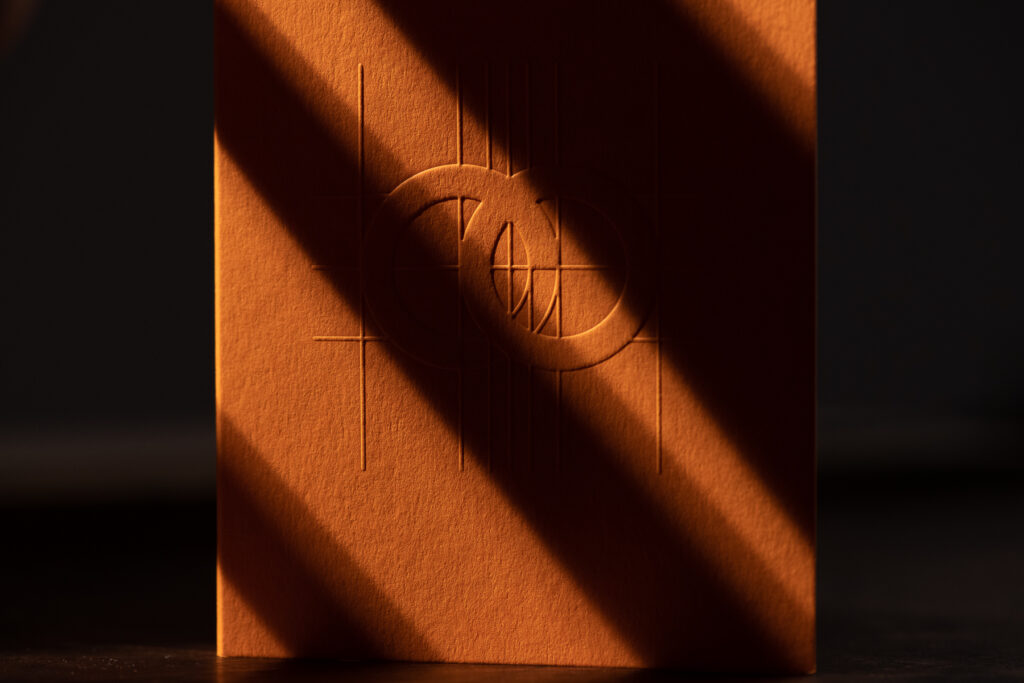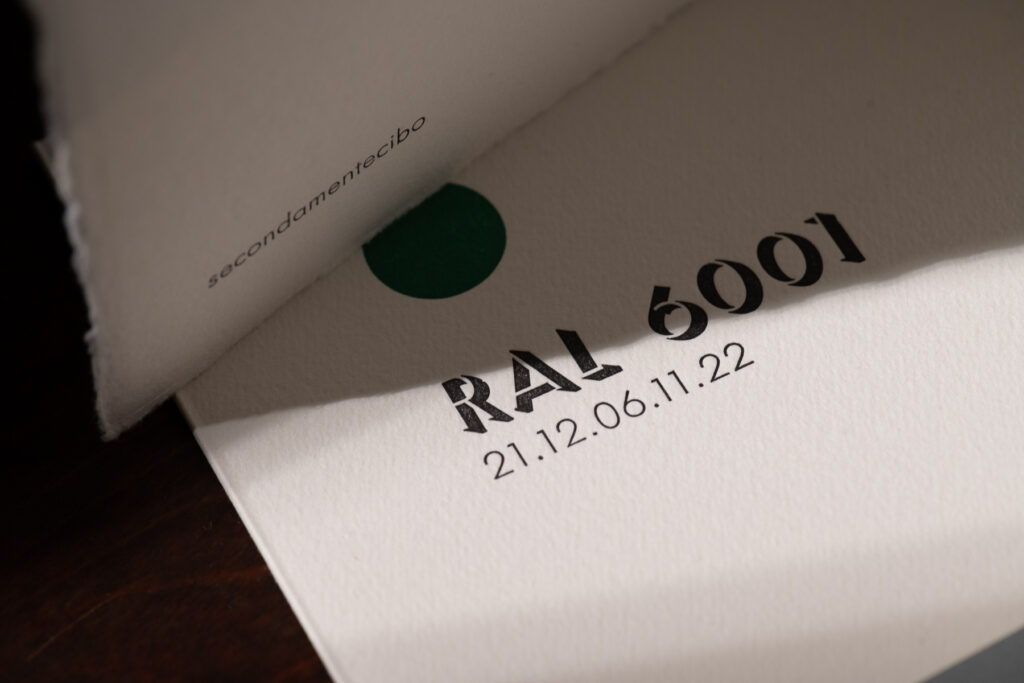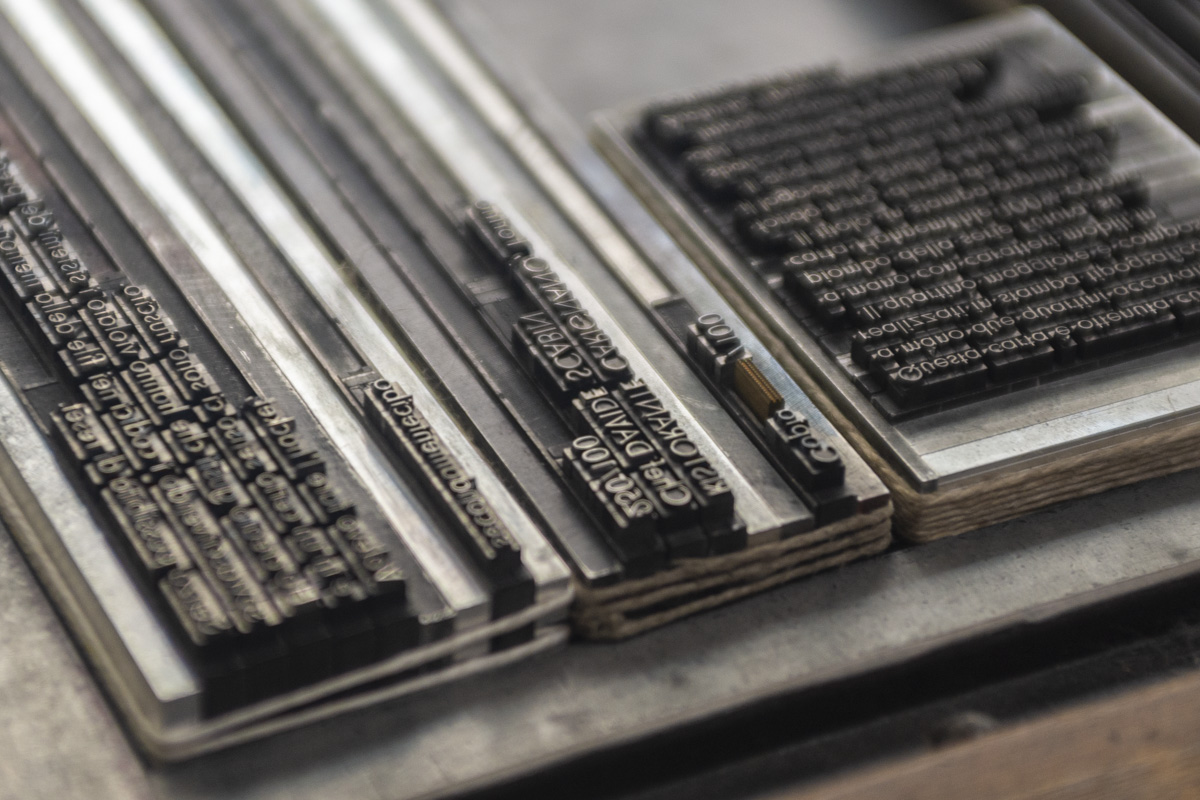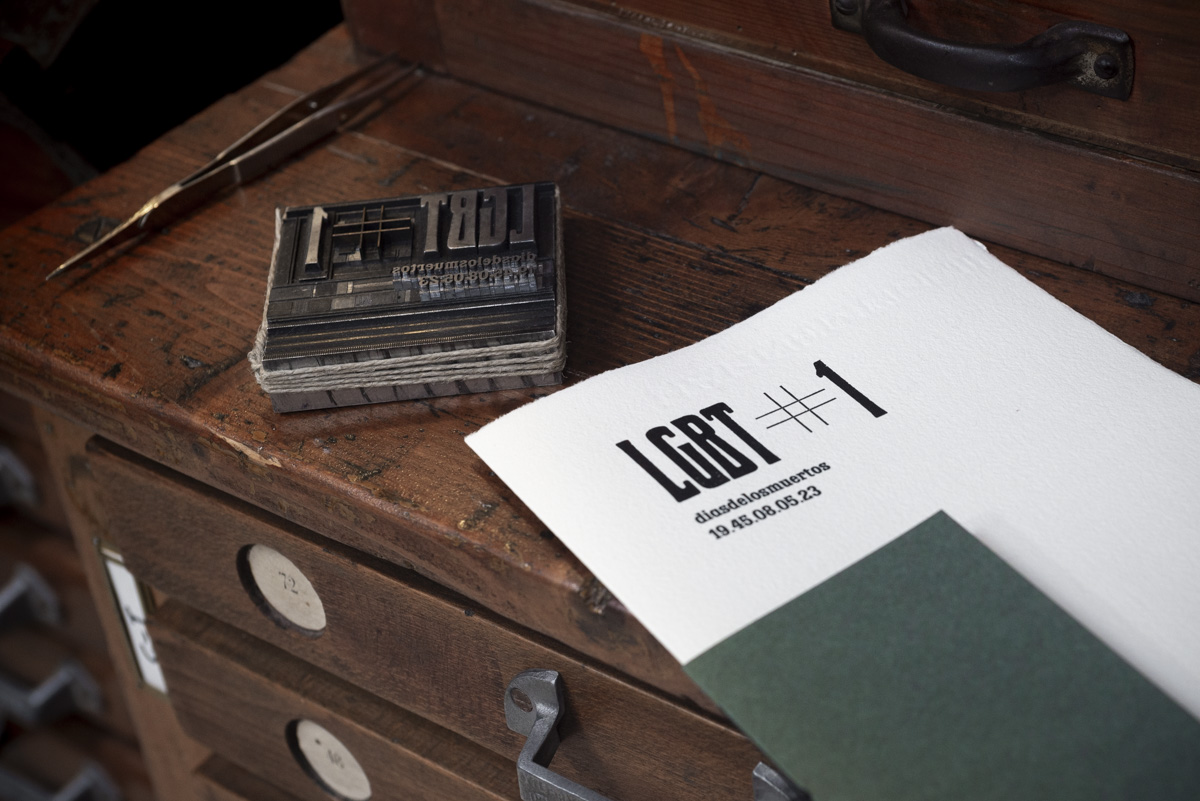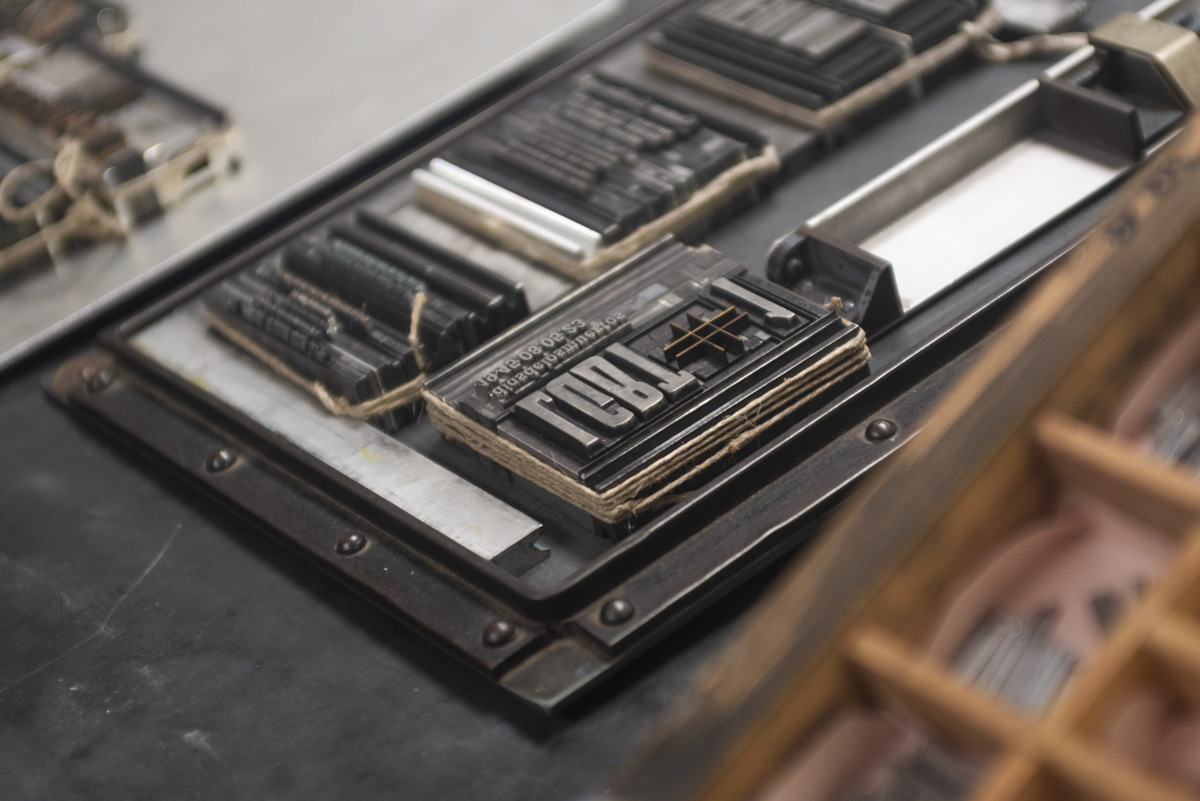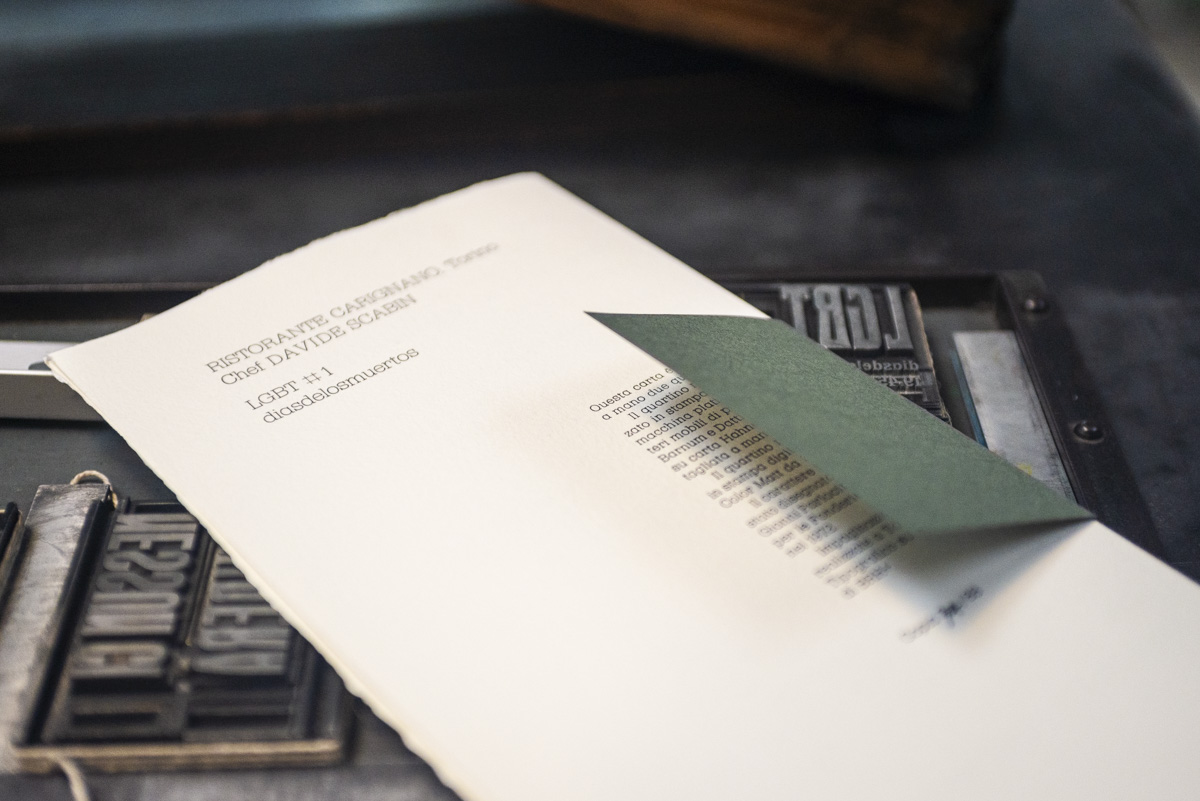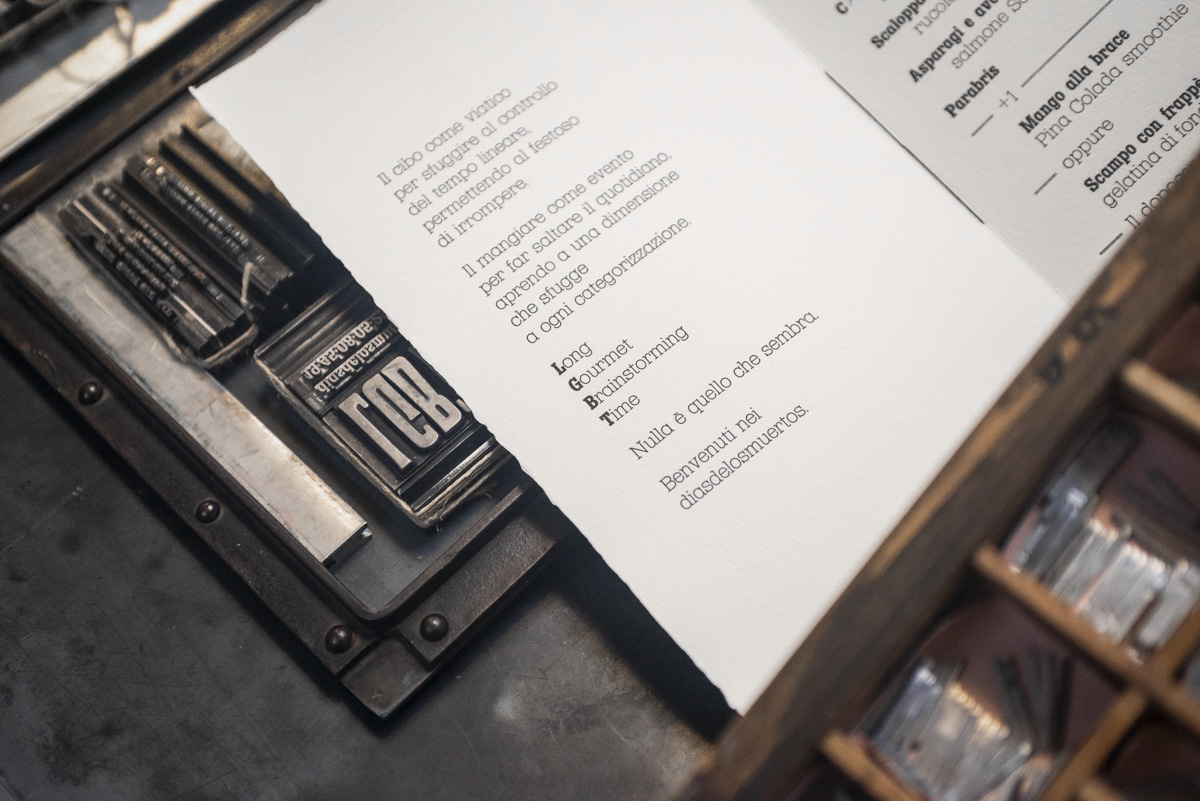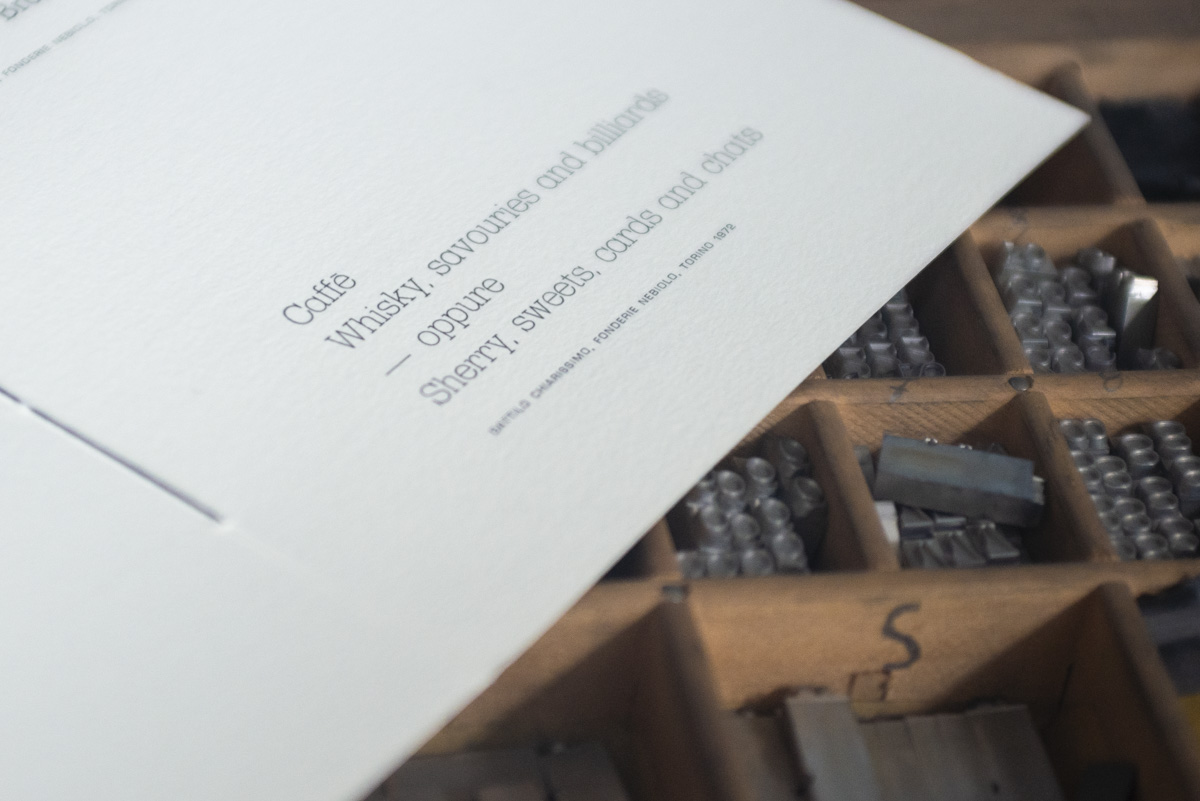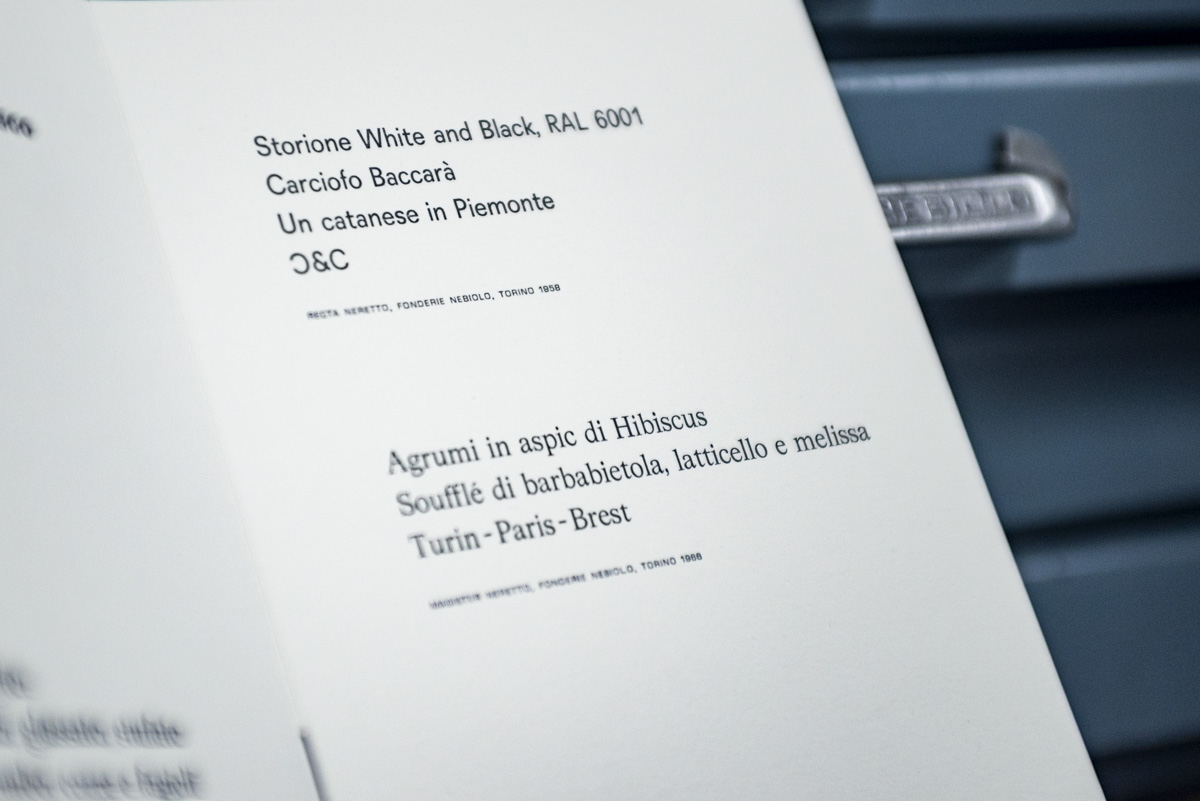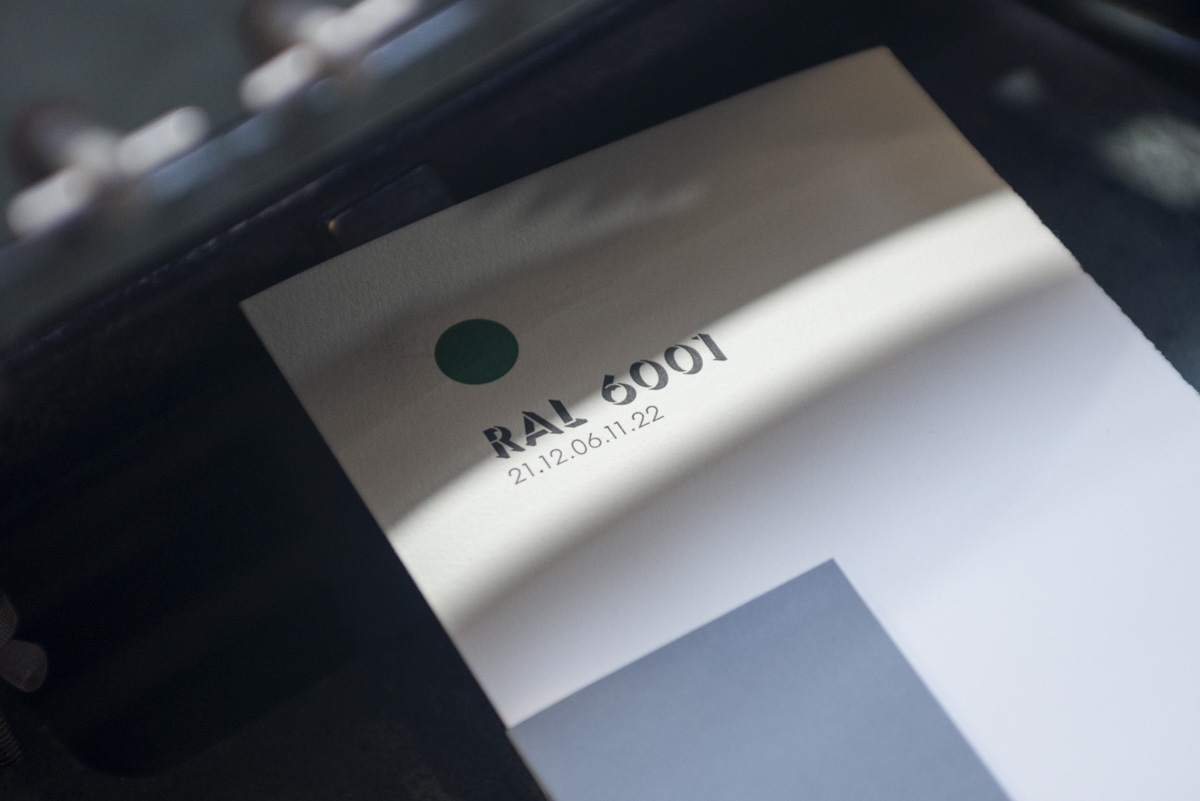
Dal 2024 Archivio Tipografico si occupa della realizzazione dei menu dello Chef Scabin per Ristorante Carignano, sotto la direzione artistica di BRH+.
Tutti i menu sono sempre interamente composti a mano con caratteri mobili in piombo o legno, su carta 100% cotone.
Riprendendo gli elementi visivi da un mondo che solitamente appartiene al mondo della stampa d’arte vengono realizzati dei menu in tiratura limitata e numerata per accompagnare chi vive l’esperienza della degustazione di una cena stellata che dura tutta la sera.